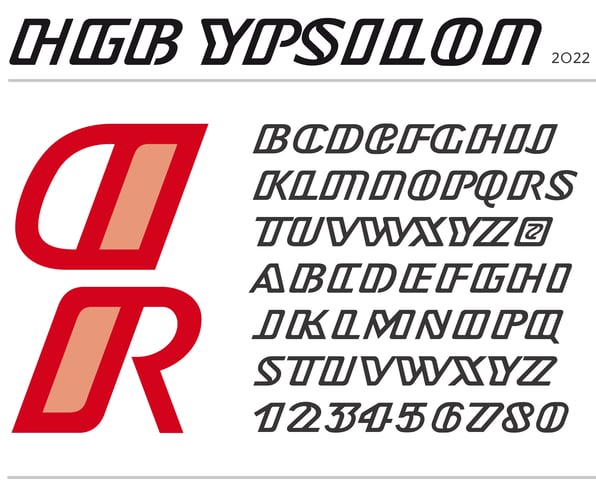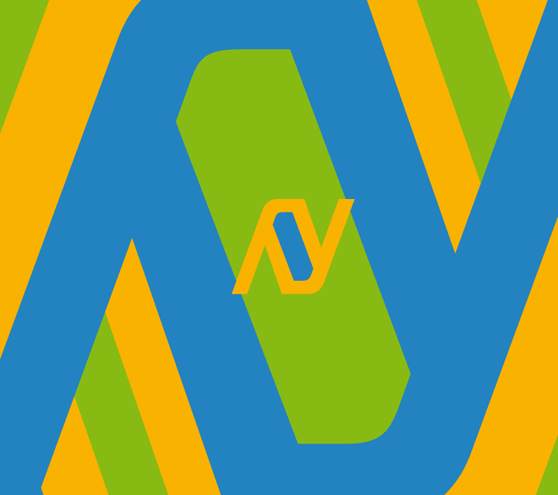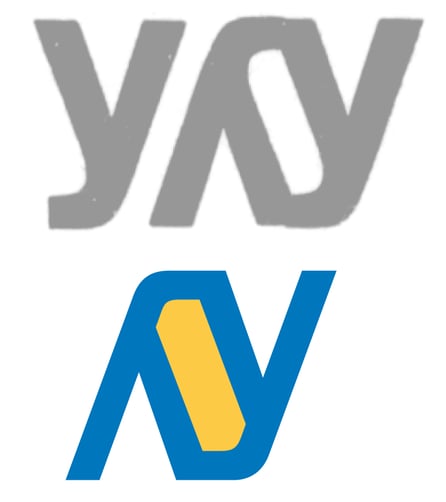
HGB Ypsilon
Eine Spielerei mit alten Anreibebuchstaben hat zu diesem Alphabet geführt. Auf den Letraset-Bogen (die älteren erinnern sich noch …) blieben immer Buchstaben übrig, die nie oder selten gebraucht wurden. ich habe manchmal Praktikant*innen damit spielen lassen. Zur Erklärung habe ich zunächst selber ein Beispiel angerubbelt. Zwei kleine y aus einer Helvetica haben diese hübsche Figur ergeben. beim genauen Hinschauen ein konturiertes, kursives N. Aus diesem N habe ich die Schrift HGB Ypsilon entwickelt. Eine reine Zierschrift – für irgendein Logo könnte sie mal interessant werden.